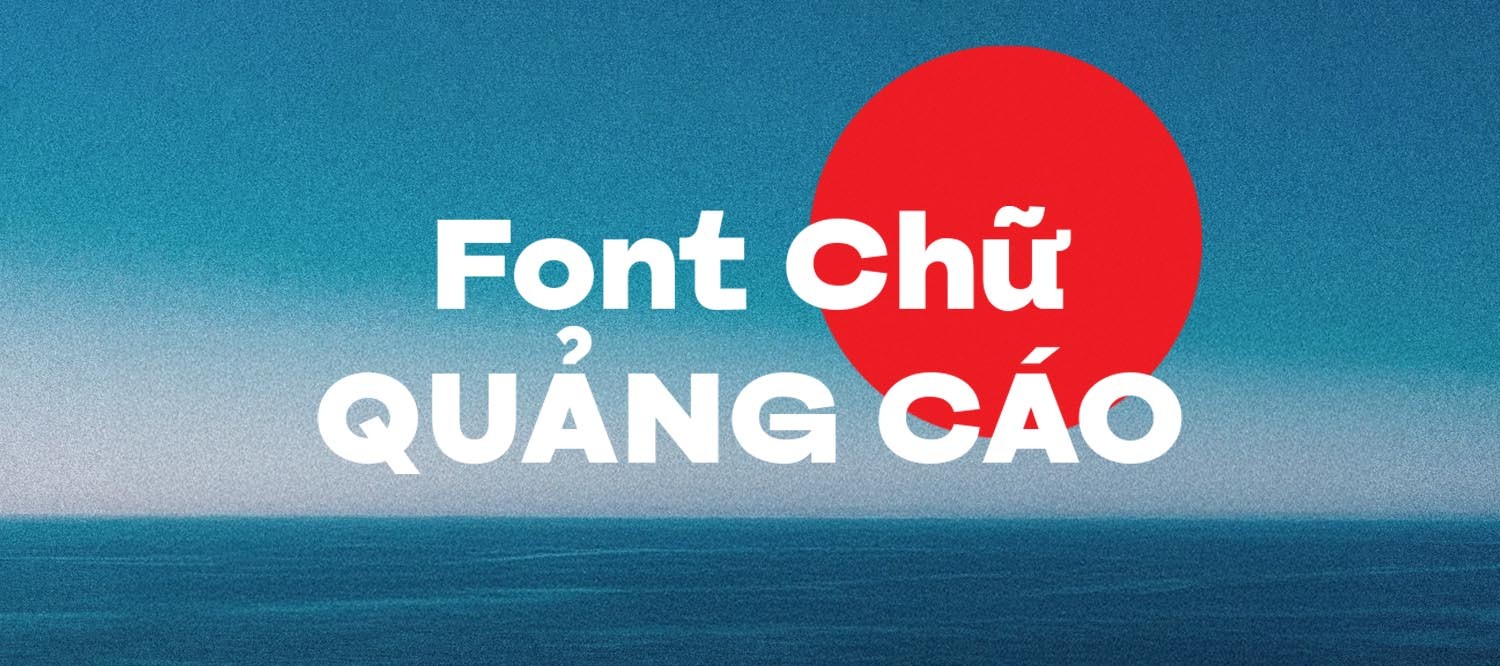
Tổng Hợp 20+ Kiểu Font Chữ Quảng Cáo Việt Hóa Cho Thiết Kế Chuyên Nghiệp
1. Giới Thiệu Chung về Font Chữ Quảng Cáo
Font chữ trong quảng cáo đóng một vai trò quan trọng không thể thiếu trong việc xây dựng hình ảnh thương hiệu và thu hút sự chú ý của khách hàng. Khi chọn font chữ phù hợp, bạn không chỉ truyền tải thông điệp hiệu quả mà còn tạo được ấn tượng sâu sắc về thương hiệu. Đặc biệt trong thiết kế biển hiệu, font chữ giúp người xem dễ dàng nhận diện và ghi nhớ thông tin quảng cáo, từ đó cải thiện hiệu quả truyền thông.
Khi lựa chọn font chữ quảng cáo, yếu tố quan trọng cần xem xét là độ dễ đọc, tính thẩm mỹ và khả năng phù hợp với thông điệp mà bạn muốn truyền tải. Font chữ không chỉ cần đẹp mà còn phải dễ dàng nhận diện từ xa, dễ đọc trên các phương tiện quảng cáo như biển hiệu ngoài trời hay các banner trực tuyến.
2. Tổng Hợp Các Loại Font Chữ Quảng Cáo Đẹp Việt Hóa
2.1 Các Font Chữ Serif Cho Biển Quảng Cáo
Font chữ serif, với các đường nét có chân ở các đầu chữ cái, tạo nên một cảm giác trang trọng và đáng tin cậy. Các font chữ này thường được sử dụng trong các thiết kế cần thể hiện sự chuyên nghiệp và sang trọng, ví dụ như trong quảng cáo của các thương hiệu cao cấp.
Font Westorn Việt Hóa
Font Westorn
mang phong cách mạnh mẽ và cổ điển, với các đường nét sắc sảo và vững chãi, rất phù hợp cho các dự án quảng cáo mang tính uy tín, như quảng cáo quân đội, bảo vệ, hoặc các sản phẩm cần thể hiện sự chắc chắn và đáng tin cậy. Font chữ này mang lại cảm giác nghiêm túc nhưng không kém phần nổi bật. Rất thích hợp cho các biển quảng cáo ngoài trời, logo công ty hoặc các chiến dịch quảng cáo đậm chất mạnh mẽ.
Font Chrone Việt Hóa
Font Chrone
là một font chữ in đậm, mạnh mẽ và dễ đọc. Với thiết kế sắc nét và rõ ràng, font này rất phù hợp cho các quảng cáo thương mại yêu cầu sự chú ý tức thì từ người xem. Font Chrone giúp tạo nên một hình ảnh mạnh mẽ và trang trọng, đặc biệt là khi được sử dụng cho các sản phẩm công nghệ, tài chính, hoặc các chiến dịch quảng cáo thể hiện sự vững chắc và hiện đại. Font này có thể được sử dụng cho các biển quảng cáo ngoài trời, banner, hoặc các ấn phẩm in ấn.
Font Born Pink Việt Hóa
Font Born Pink
lấy cảm hứng từ nhóm nhạc nổi tiếng Blackpink, với thiết kế trẻ trung và năng động. Font chữ này có các đường nét mượt mà nhưng không kém phần sắc sảo, tạo cảm giác hiện đại và thời trang. Được tối ưu hóa cho các quảng cáo nhắm đến đối tượng trẻ, font Born Pink rất phù hợp cho các chiến dịch quảng bá liên quan đến âm nhạc, sản phẩm thời trang hoặc các sự kiện giải trí. Font này giúp tạo dựng hình ảnh năng động và đầy sức hút.
Font TH Cungcap 12 Mạnh Mẽ Việt Hóa
Font TH Cungcap 12
là một kiểu font chữ mạnh mẽ, hiện đại với các đường nét sắc sảo và độ dày vừa phải, tạo cảm giác vững chắc và dễ đọc. Đây là font chữ lý tưởng cho các chiến dịch quảng cáo yêu cầu sự mạnh mẽ và dễ nhận diện. Font này có thể được ứng dụng trong các quảng cáo ngoài trời, logo thương hiệu, hoặc các chiến dịch đậm tính công nghiệp. Font giúp làm nổi bật thông điệp về sự bền bỉ và uy tín.
Font Luxury 3 Việt Hóa
Font Luxury 3
mang lại cảm giác sang trọng và tinh tế. Được thiết kế với các đường nét thanh thoát và mượt mà, font này thích hợp cho các dự án quảng cáo cao cấp, như các sản phẩm thời trang, ô tô, hoặc các sự kiện sang trọng. Font Luxury 3 dễ dàng tạo dựng hình ảnh đẳng cấp và uy tín, giúp thu hút khách hàng mục tiêu cao cấp. Các chiến dịch quảng cáo sử dụng font này sẽ mang lại ấn tượng mạnh mẽ và tinh tế.
2.2 Các Font Chữ Sans-Serif Cho Biển Quảng Cáo
Font chữ sans-serif, không có các chân ở các đầu chữ cái, mang lại vẻ hiện đại và dễ đọc hơn, đặc biệt là trong các thiết kế quảng cáo ngoài trời. Font sans-serif thường được sử dụng trong các biển quảng cáo ngoài trời vì chúng dễ đọc từ xa và trên nhiều nền tảng khác nhau.
Font TH Degrad Mono Việt Hóa
Font TH Degrad Mono
là một kiểu font chữ công nghệ, hiện đại, với thiết kế đơn giản nhưng đầy ấn tượng. Font này không có các chi tiết trang trí, mang đến vẻ đẹp sạch sẽ và dễ đọc, rất phù hợp cho các quảng cáo về công nghệ, phần mềm hoặc các sản phẩm kỹ thuật số. Với tính năng dễ dàng kết hợp với các yếu tố thiết kế khác, font này thường được sử dụng trong các chiến dịch quảng cáo công nghệ hoặc các thương hiệu đột phá.
Font TH Wolgen Việt Hóa
Font TH Wolgen
Tổng kết: Bài viết đã tổng hợp các font chữ quảng cáo đẹp và hữu ích, giúp bạn lựa chọn đúng font chữ cho các chiến dịch quảng cáo, từ biển quảng cáo ngoài trời đến quảng cáo online. Hãy áp dụng những lời khuyên trong bài viết để thiết kế biển hiệu ấn tượng và hiệu quả!